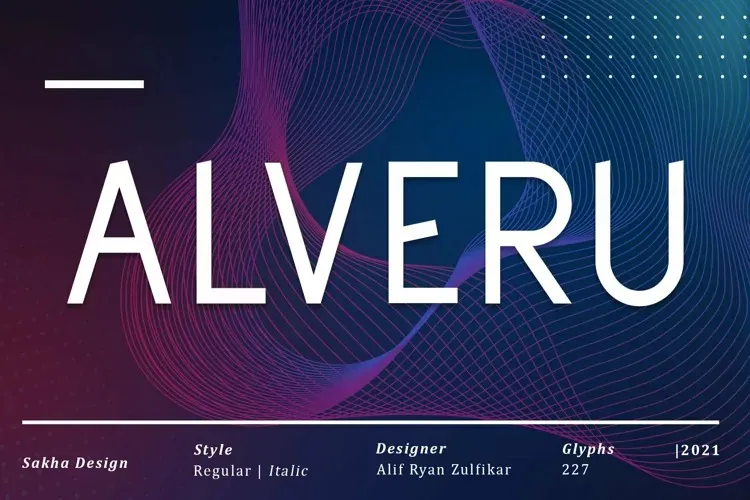
A Alveru Font é uma elegante fonte sans-serif projetada pela Sakha Design que traz a conveniência de um corpo levemente sólido e uma leitura confortável, ideal para projetos variados. Suas linhas limpas e simples permitem facilmente sua integração em uma ampla gama de ideias criativas, fazendo com que suas aplicações se destaquem ainda mais. Seja para gráficos publicitários, design editorial ou qualquer outro tipo de projeto visual, a Alveru Font traz clareza e modernidade aos seus esboços digitais. Com sua estrutura sólida e leitura agradável, não apenas complementa suas ideias visuais, mas as fazem se destacar no meio do ambiente digital.